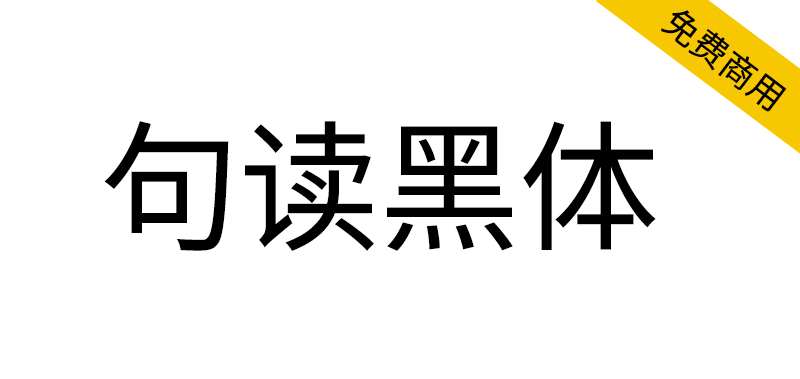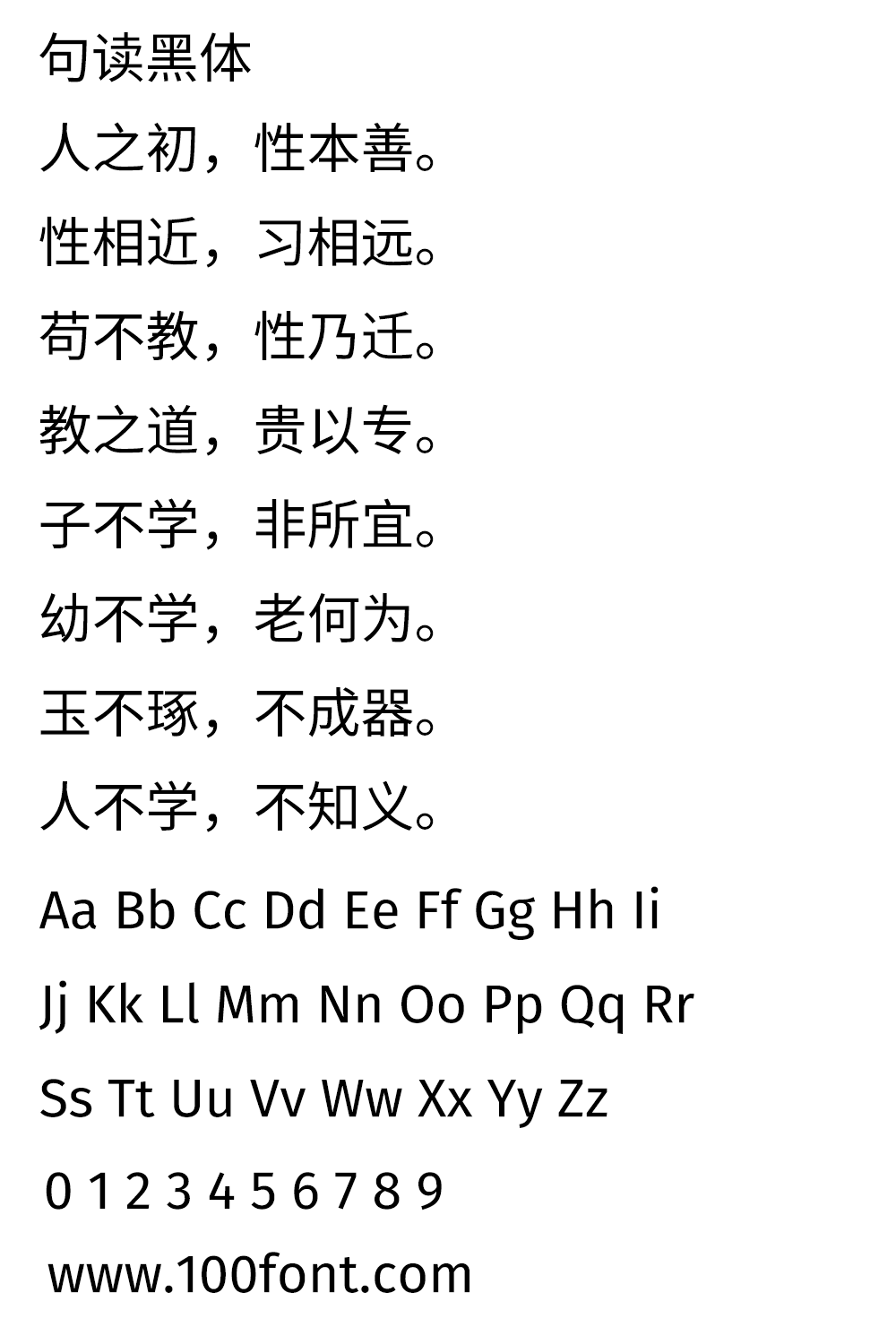
句读黑体,支持多种语言文字的商用免费开源黑体,基于更纱黑体、思源黑体、尙古黑体、Noto Traditional Nushu、KhaWa Sans和FiraGO。
支持的文字:汉字、假名、谚文、女书、藏文、拉丁文扩展、西里尔文扩展 (包含塞尔维亚语和保加利亚语的 Opentype locl 特性)、希腊文扩展、国际音标、阿拉伯文、天城文、格鲁吉亚文、希伯来文、泰文。